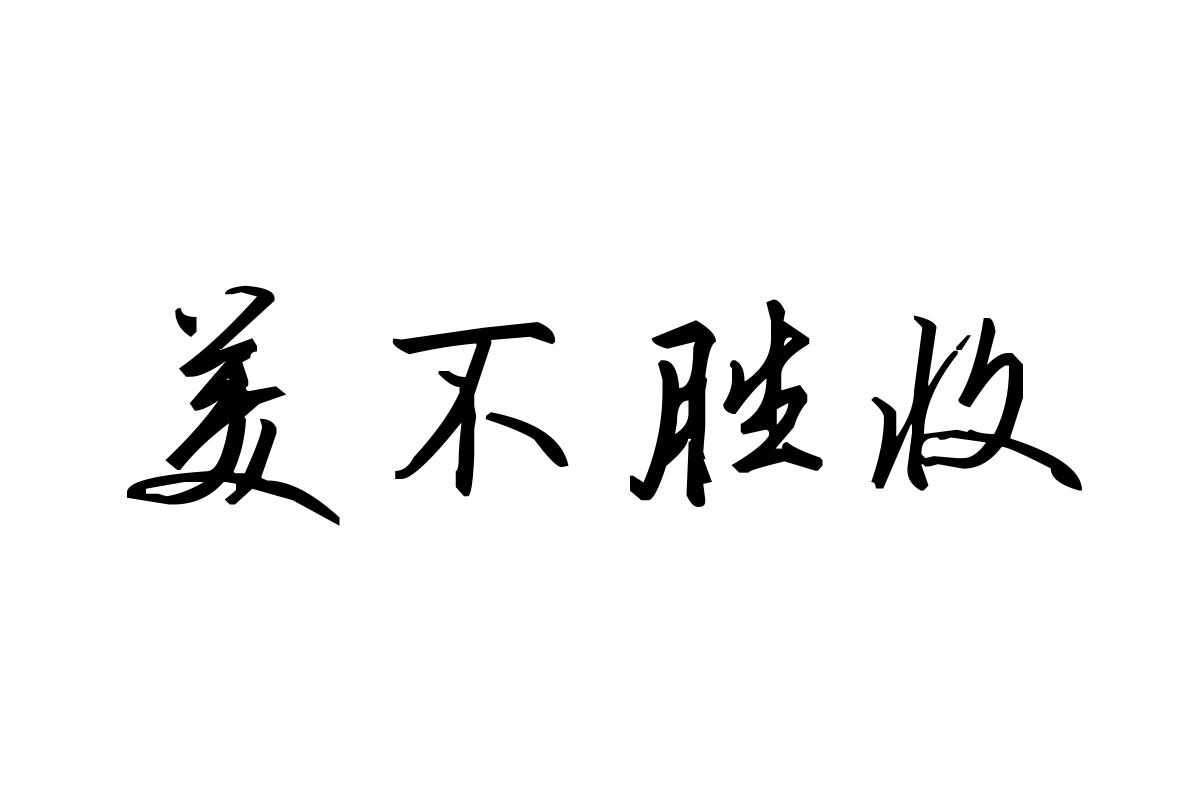
米开诗语行楷字体是一种独特的中文书法字体,由著名书法家米开诗创作。这种字体以其流畅、优美的线条和独特的结构而著称,给人一种宁静、和谐的感觉。
米开诗语行楷字体的特点如下:
1. 笔触流畅:这种字体的笔画流畅自然,没有过多的装饰和修饰,给人一种简洁、清新的感觉。
2. 结构独特:米开诗语行楷字体的结构独特,每个字的笔画都有一定的规律和节奏,使得整体看起来非常协调和统一。
3. 风格鲜明:这种字体的风格鲜明,既有传统的韵味,又有现代的气息,适合用于各种场合的书写和设计。
4. 适用广泛:米开诗语行楷字体适用于各种类型的文档和出版物,无论是正式的文件还是个人的创作,都能找到合适的表达方式。
总之,米开诗语行楷字体是一种具有独特魅力的中文书法字体,其流畅的线条、独特的结构和鲜明的风格使其在众多字体中脱颖而出,值得一试。